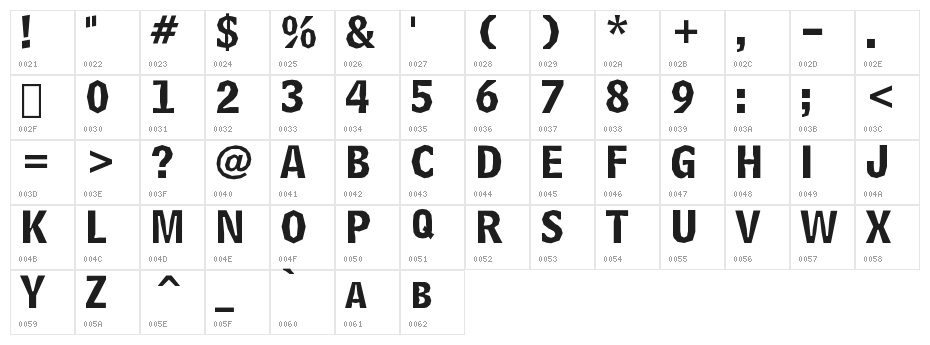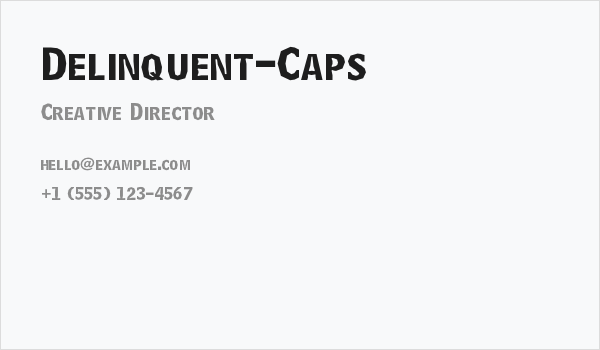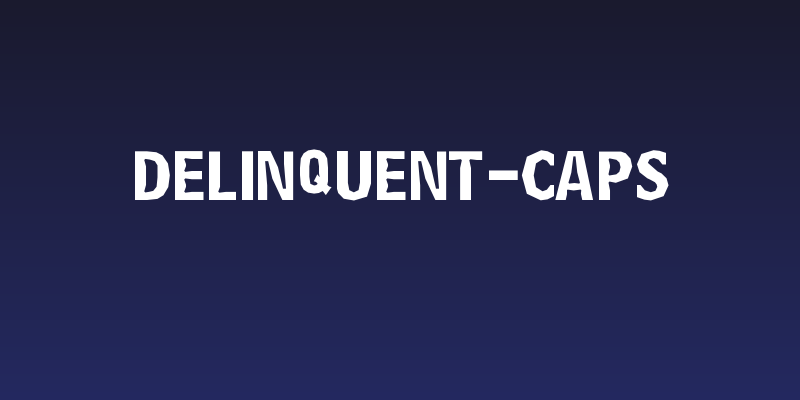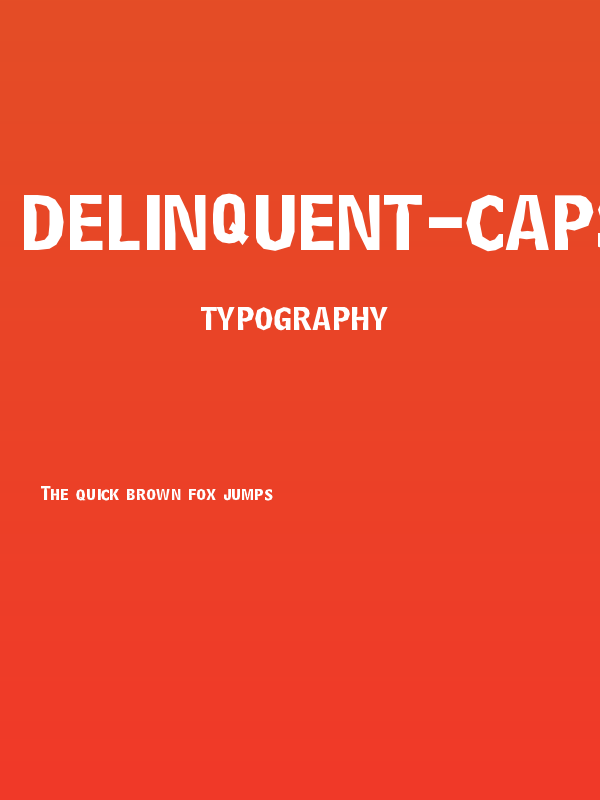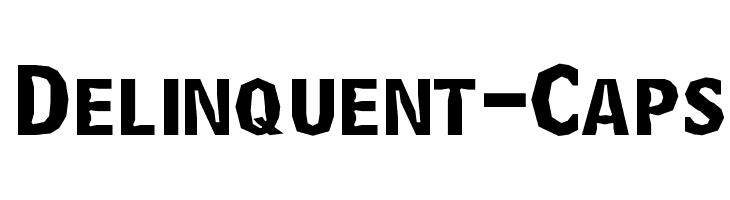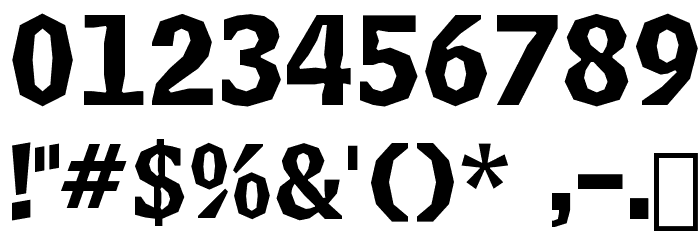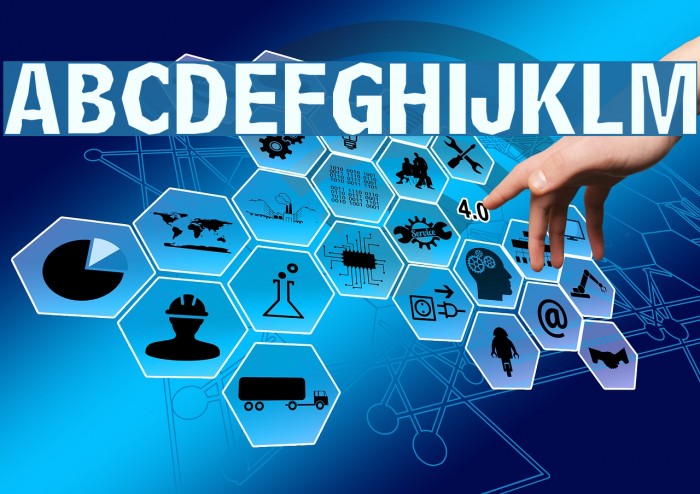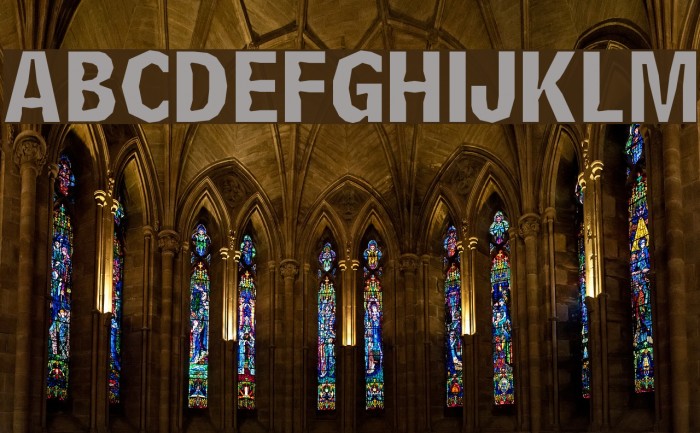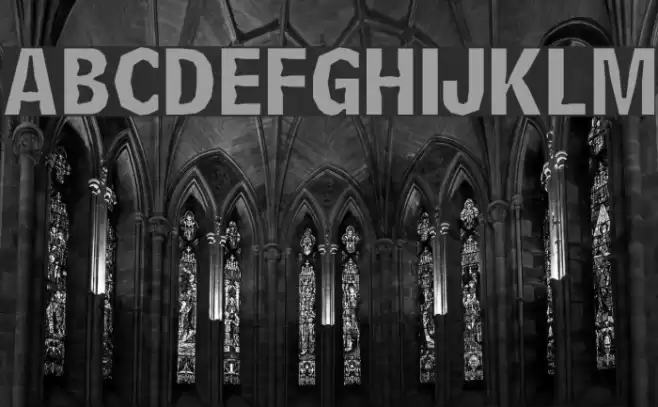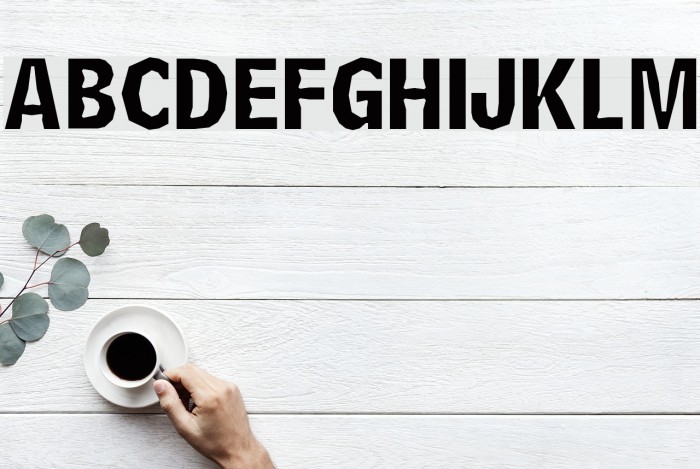
Delinquent-Caps Font
| Stil general | Modern, Edgy |
| Proiecte propuse | Ideal for posters, album covers, streetwear branding, and any project needing a bold, rebellious look. |